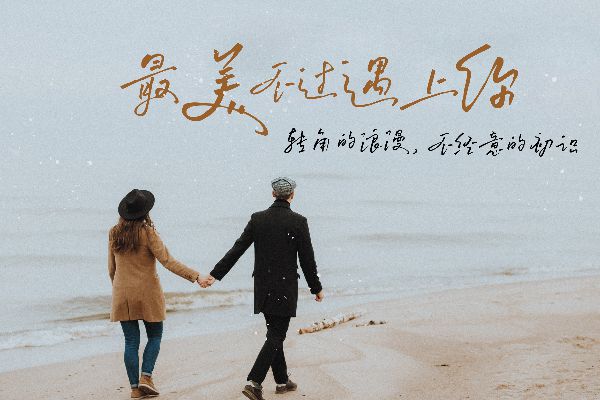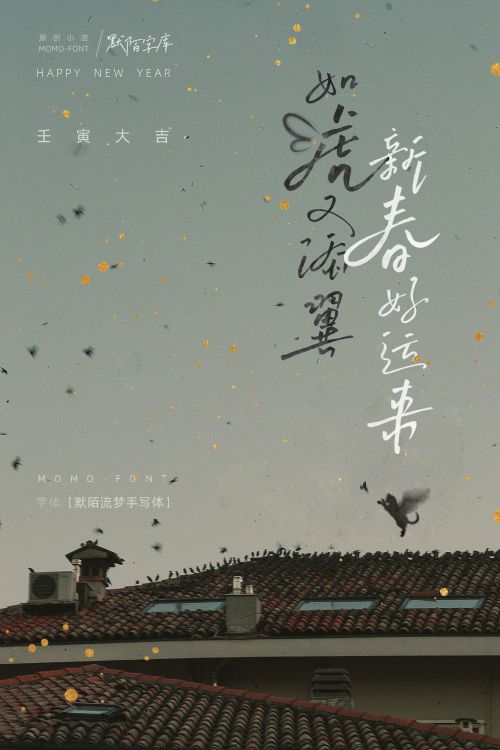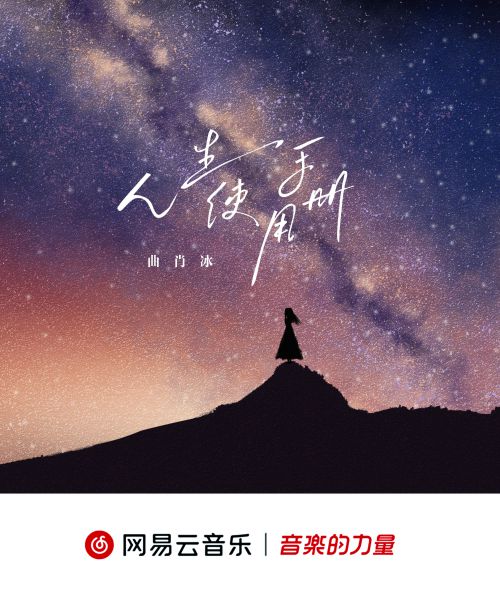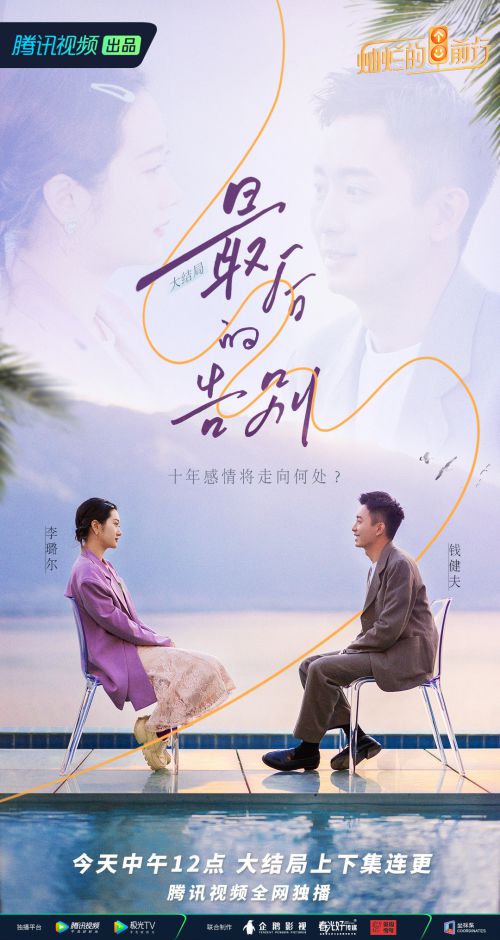
默陌流梦手写体
默陌流梦手写体是一款钢笔手写字体,笔触轻松流畅,字形舒展优美,整体融入英文手写的流线形态,用灵动的线条赋予字体随性自由的个性。
默陌
默陌是一名独立设计师,从事字体创意设计多年,目前已发布默陌水墨手迹系列、默陌硬笔手写体系列、默陌奇趣可爱手写系列等30余款字体字库作品,广泛应用于平媒、影视、手机端显示等场景。默陌字体字形多变,风格多元,坚持致力于传统书法意趣和现代手写个性的有机融合,创作出更多美好的原创手迹。